黑板报相信大家都有所接触过,我们在学校的时候每个班肯定都会有一块黑板,专门用来做板报的。等我们进入社会踏入公司工作,也会有专门用来宣传的黑板报,因此我们在制作黑板报时需要的黑板报字体就成了关键。
我们知道的黑板报字体都是用来制作黑板报的,其实他的用途不光是这个哦,我们甚至可以用黑板报字体来进行一些海报或者广告的制作,因为用这种字体制作出来的话,我们不光会有童年学生时代的回忆,甚至还会有一些独特创新的滋味,毕竟广告用了其他类型的字体可是很少见的。
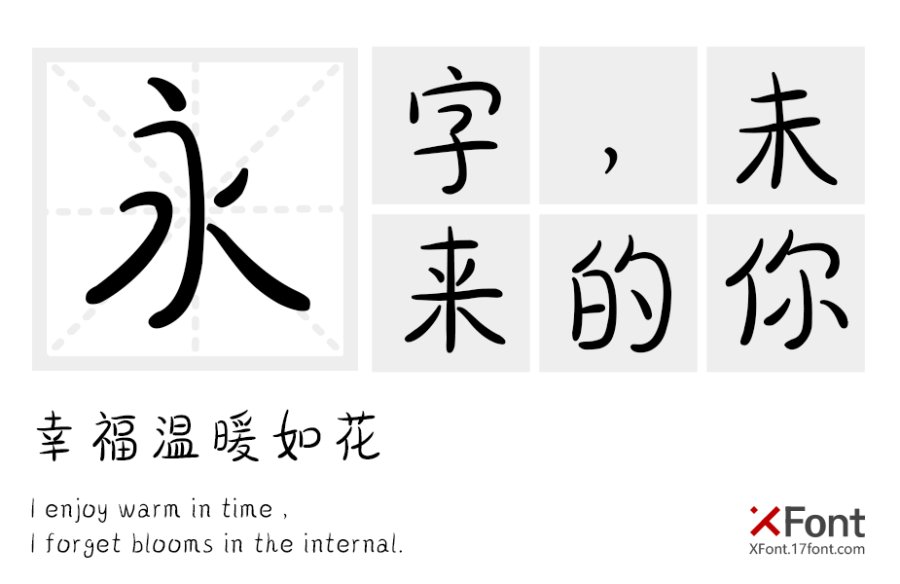
为什么说xfont字库能给你最好的黑板报字体呢?你可以在网上搜索一下,看看我们xfont字库的介绍,你就能知道我们是专门创作手写字体的一家字库,我们的职能就是手写字体,而我们需要的黑板报字体也是我们手写内容其中的一份子,因为黑板报也是需要用手来进行操作的,所以我相信xfont字库中的黑板报字体绝对是领先与其他的。